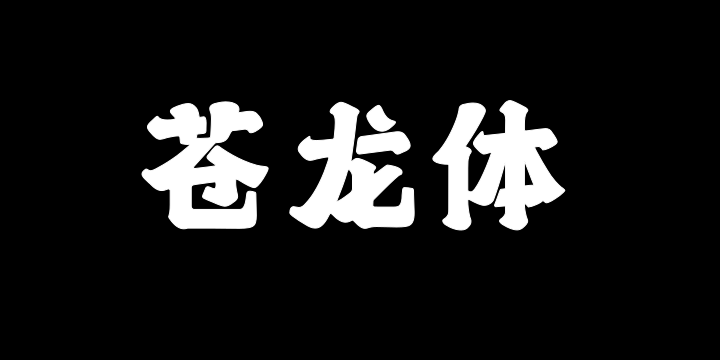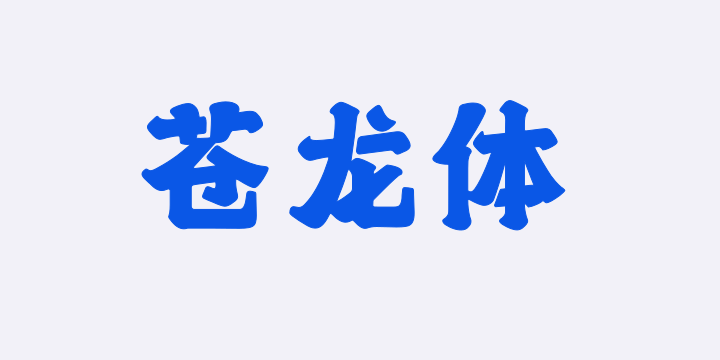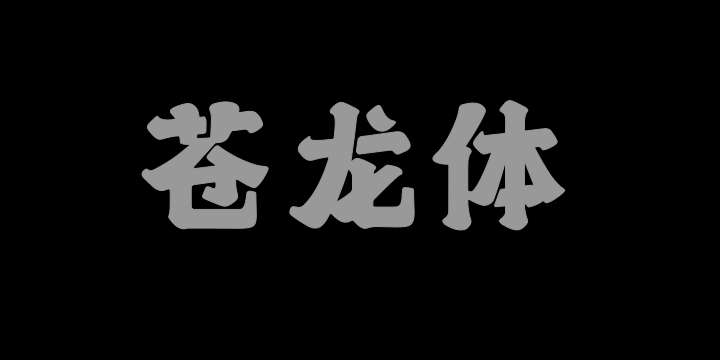
上首苍龙体 By 上首造字 商用字体
字体全名: 上首苍龙体
铸字厂: 上首造字
设计师: 胡博剑
字体简介: 上首苍龙体,简体中文约6763字,字体字型饱满,观感大气。保证识别性的前提下增加断口设计,使其具有独特的外观。字体连接处进行圆角处理,带来了全新的视觉感受。适用于搭配标志、广告标语、商业广告等高端属性。